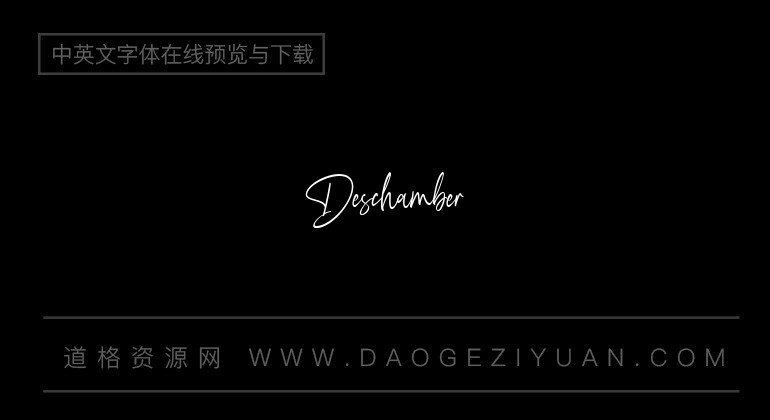
Deschamber
Deschamber 字体是一款极简风格的英文字体,由设计师 Andréa Magalhães 创作。它拥有简约、细腻的外观,可以让文字拥有更加精致的感觉。Deschamber 字体的字符结构比较简单,它的字体高度和宽度均有一定的比例,使得文字的可读性得到了很大的提升。它的字体特色是曲线精细、线条细腻,在文字中可以提高文字的精致感。
Deschamber是一款非常不错的手写艺术字体,具有很好的视觉感,适合于文化类的宣传设计、商业类品牌的广告和产品包装设计以及个性化文字排版等较多场景。
Deschamber字符映射图